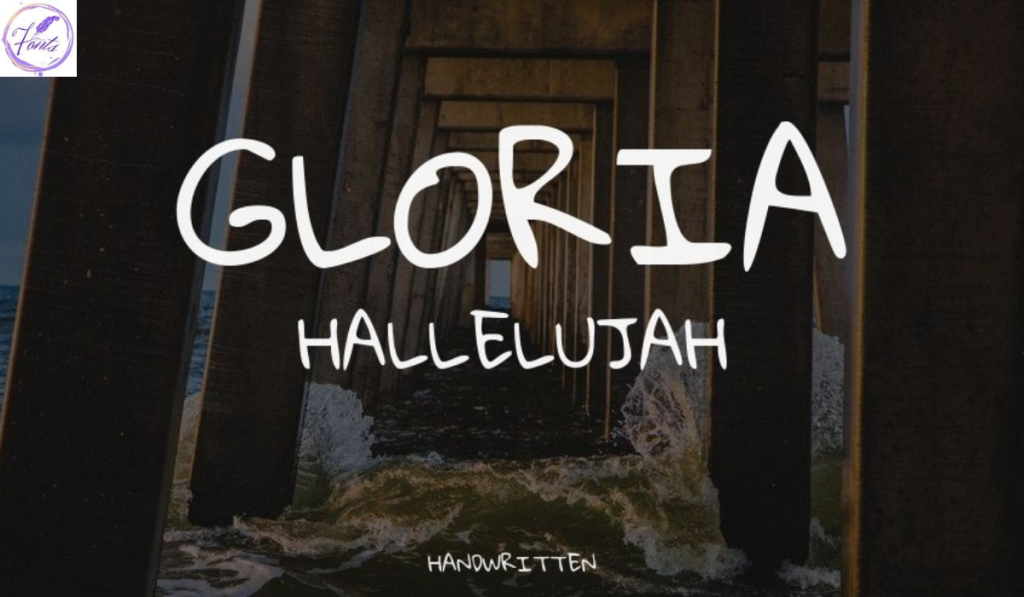
Gloria font việt hóa
Tác giả: Gloria Sanchez
Ngày phát hành: 2019
Ngôn ngữ: Tiếng Việt, nhiều ngôn ngữ khác
Bộ Font: Gloria
Phân loại: Cá tính, độc đáo
Kiểu chữ: Không chân
Độ dày: Regular, Highlight
Gloria font là một kiểu chữ đầy phong cách và sang trọng, được ra mắt lần đầu vào năm 2019 bởi Gloria Sanchez. Với những đường nét thanh thoát và tinh tế, gloria font mang đến vẻ đẹp cổ điển nhưng không kém phần hiện đại. Đây là font chữ lý tưởng cho các thiết kế thiệp mời, bìa sách, và các dự án cần sự thanh lịch và quý phái. Khả năng Việt hóa tuyệt vời của font này giúp người dùng dễ dàng áp dụng trong các dự án tiếng Việt mà không gặp khó khăn gì.
Đánh giá gloria font
Gloria font nhận được rất nhiều phản hồi tích cực từ cộng đồng thiết kế. Với sự pha trộn hoàn hảo giữa cổ điển và hiện đại, font này không chỉ đẹp mắt mà còn rất dễ đọc. Điều này làm cho gloria font trở thành lựa chọn hàng đầu cho những dự án yêu cầu tính thẩm mỹ cao. Khả năng Việt hóa xuất sắc của font cũng là một điểm cộng lớn, giúp người dùng dễ dàng tích hợp vào các thiết kế tiếng Việt. Nếu bạn đang tìm kiếm một font chữ vừa thanh lịch vừa dễ sử dụng, gloria font chắc chắn sẽ không làm bạn thất vọng.